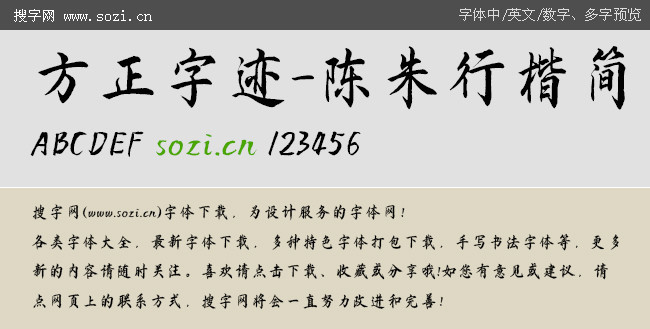
方正字跡-陳朱行楷簡(jiǎn)
搜字網(wǎng)提供一款方正字跡-陳朱行楷簡(jiǎn)中文字體下載,陳朱行楷簡(jiǎn)字體端莊、穩(wěn)重、大氣,具有很輕的視覺感染力,該字體的創(chuàng)作也是融合唐人楷書和“二王"行書特點(diǎn),即有唐楷的端莊、嚴(yán)謹(jǐn),也有"二王"行書的古雅、俊秀,是作者學(xué)習(xí)傳承祖國(guó)傳統(tǒng)書法藝術(shù)的一個(gè)成果。適合應(yīng)用于藝術(shù)設(shè)計(jì)、平面宣傳設(shè)計(jì)、網(wǎng)頁(yè)設(shè)計(jì)、書籍雜志哦,書法字帖等領(lǐng)域。